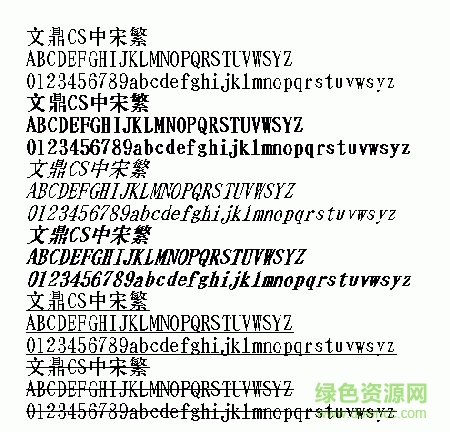
宋體字于明朝以后才出現,那何以謂作“宋體”?原來,宋朝文化鼎盛,宋刻本精美大氣,具有很高的收藏價值,明朝文人特別是書籍的收藏者,極度推崇“宋刻本”,因此明代出版界多翻刻宋刻本,但為求便捷,也為了降低成本,明朝的這些仿宋刊本經常只刻出“膚廓字樣”,而非原來楷味濃厚的宋字。最終形成了一種專門用于印刷的字體??滴跏辏ü?673年),敕廷臣補刊經庵《文獻通考》的序文中,規(guī)定:“此后刻書,凡方體稱宋體字,楷書均稱軟字”。“宋體”之名由此而來。
但由于此字體盛行于明朝,并在明朝時期傳入日本,因此日本于19世紀制造鉛字字模時,稱此字體為“明朝體”,及至20世紀中葉,從鉛字凸字排版過渡到照相排版時,臺灣從日本引進照相排版及相關字模,連帶引進“明體”一詞,臺灣華康科技于八十年代制作電腦字型時,也以“明體”作稱呼,但在臺灣教育部官方則稱為“宋體”,因此臺灣教育部所編定的字體稱為“教育部標準宋體”。故雖然香港稱之為“明體”,在中國大陸、臺灣教育部稱為“宋體”,但兩者只是名稱上的不同。